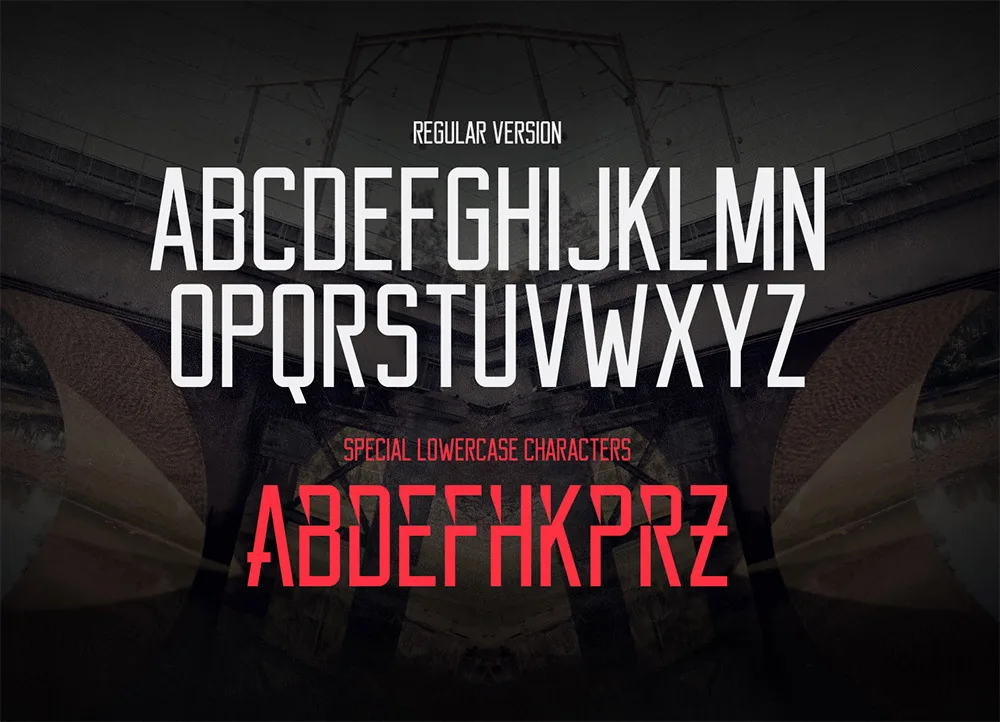
15 tipografias para escrita em caixa alta
Conseguir encontrar estilos de fontes em caixa alta para o seu projeto, seja ele qual for, as vezes pode se tornar uma tarefa um pouco difícil, já que com tantas opções disponíveis na internet, procurar pode consumir o todo o seu dia.
Reunimos abaixo algumas opções, na verdade 15 opções, de tipografias em caixa alta, criativas, modernas, sensacionais, para que você possa usar, aproveitar, se inspirar e o principal, não perder tanto tempo assim.
Bellaboo
Bellaboo é ótimo para as manchetes e títulos. O download gratuito vem com várias versões de arquivos, incluindo OTF, TTF, e formatos de fontes web (EOT, WOFF, WOFF2). Pode ser usados para os seus projetos pessoais e comerciais.
Bernier
Perfeito se você estiver partindo para o design gráfico do vintage com temas tais como emblemas, logótipos, e outros projetos. Eles também são permitidos para seus projetos pessoais e comerciais
Reckoner
Pode ser usado para adicionar um novo estilo para seus títulos e manchetes. Também estão disponíveis para o projetos pessoais e comerciais.
Smaq
Com um total de 8 estilos diferentes que podem ser utilizadas para cartazes e outros projetos de design gráfico.
Uni Sans Free
Com estilos regulares e itálico, possui um total de 4 caracteres tipográficos em formato OTF. Estes podem ser utilizados para modelos comerciais e pessoais.
Che’s Bone
Manteka
Contém todas as letras e números alfabéticos, bem como alguns dos símbolos também. Pode ser usado para cabeçalhos, títulos e legendas.
Mohave
Completa, com os alfabetos (incluindo acentos), números e mais das pontuações e símbolos.
Markfreer
Contém todas as letras e números, mas não tem pontuações. Pode ser usado em seus títulos ou manchetes e pode ser baixado em formato OTF e TTF.
Intro Condensed Free
Moderne Sans
Sem serifa pode ser usado livremente em seu projeto pessoal e comercial.
Simplifica
Para seus títulos e legendas. Ela é projetada com uma linha fina constante que faz com que seja agradável aos olhos.
Fancy Me
Fonte serif com uma aparência feminina e pode ser usado para trabalhos pessoais ou pessoais.
Glamor
Este tipo de letra pode ser usado para as manchetes, subtítulos e títulos também. Você pode baixar o seu formato OTF e TTF gratuitamente.
Adam.Cg Pro
Uma fonte sem serifa que exibe um design limpo e nítido, o que é perfeito para os títulos e manchetes. Este estilo de fonte pode ser usado para projetos pessoais.